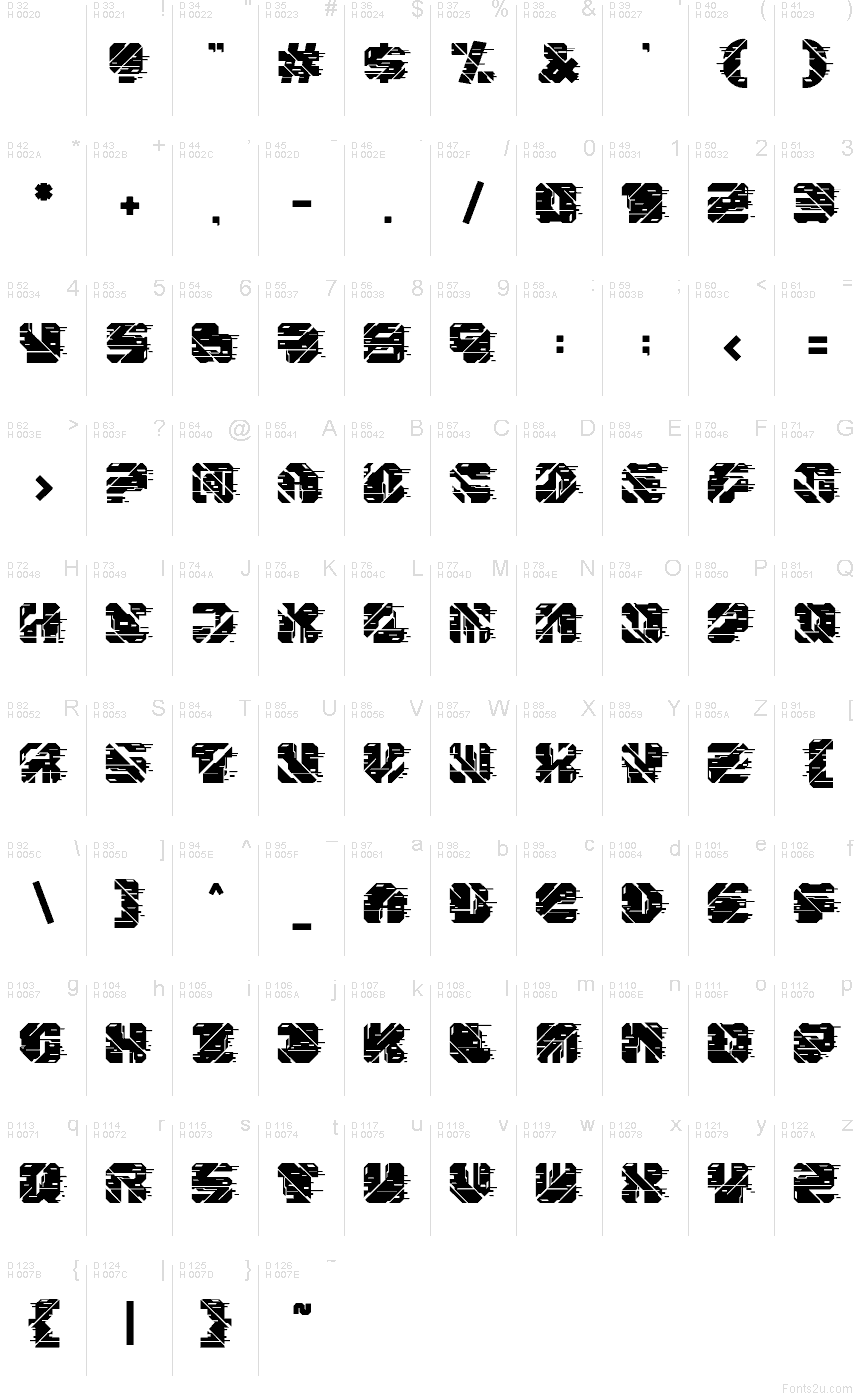
Space Sparkle Four od Putracetol Studio je bezplatné, futuristické písmo typu display, které definují rozbité vodorovné pruhy a ostré diagonální řezy. Každé písmeno tak vypadá, jako by bylo rozseknuto skenovacími čarami. Tato opakující se fragmentace dodává designu neklidný, digitální rytmus, přičemž plné černé tvary jsou přerušeny přesně tak, aby evokovaly rychlost, šum signálu a mechanický pohyb.
Plakáty, e-sportovní grafika, názvy her, sci-fi obaly či nadpisy technologických akcí – to vše tomuto písmu svědčí, zejména pokud váš layout vyžaduje výrazný grafický prvek namísto neutrálního písma. Pruhované přerušení udržuje krátká slova dynamická na obrazovce i v tisku a umožňuje dodat říz logům, streamovacím překryvům i promo bannerům bez nutnosti dalších efektů.